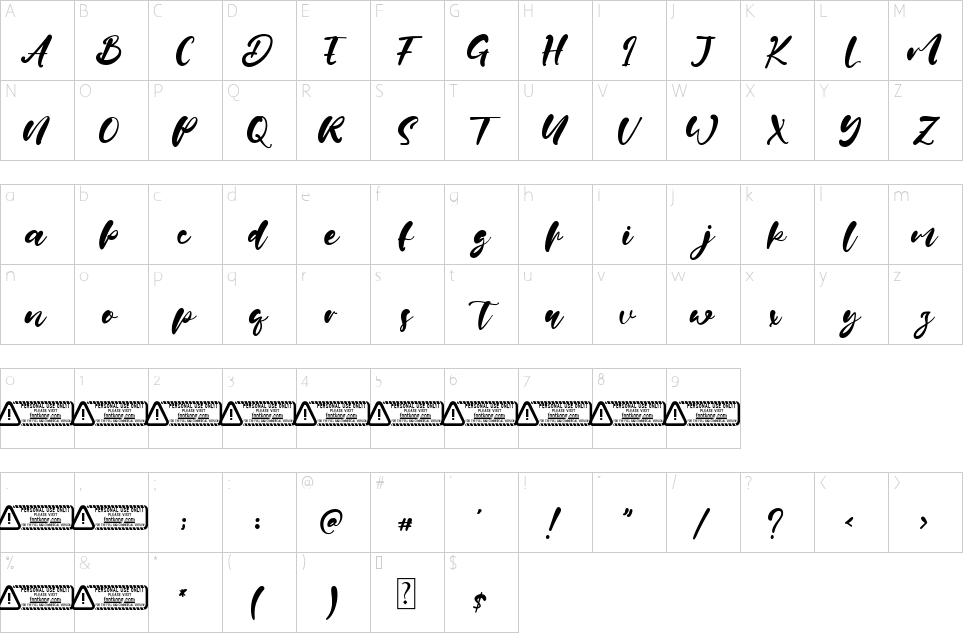
A fonte Jane Hans, criada pela Font Kong, é uma delícia para os amantes de letras gráficas. Ela foi projetada para fornecer um estilo único e agradável que encaixa-se perfeitamente em diversas aplicações, desde o design gráfico até a criação de materiais publicitários. Esta fonte, disponível tanto para Windows quanto para Mac, se destaca pela sua simplicidade e eficiência, sendo o tipo ideal para quem busca uma fonte clara e elegante. Com 3.967 downloads, já mostrou a sua relevância e qualidade para os designers de todo o mundo. Se você está procurando por um tipo de fonte que seja simples de usar e com um visual atraente, Jane Hans pode ser a fonte perfeita para você. Descubra o poder da Jane Hans e veja por si mesmo!